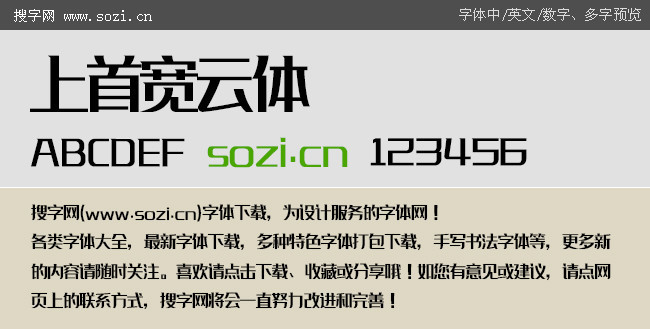
上首寬云體
搜字網(wǎng)給大家提供一款上首寬云體中文字體下載,上首寬云體,字體風(fēng)格穩(wěn)重呈方塊形,字體筆畫(huà)豎折處細(xì)節(jié)處理,是此套字庫(kù)的亮點(diǎn)。字庫(kù)整體特征堅(jiān)硬、有力,具有現(xiàn)代、國(guó)際化的指向性,適用于搭配標(biāo)志、廣告標(biāo)語(yǔ)、商業(yè)廣告等高端屬性。